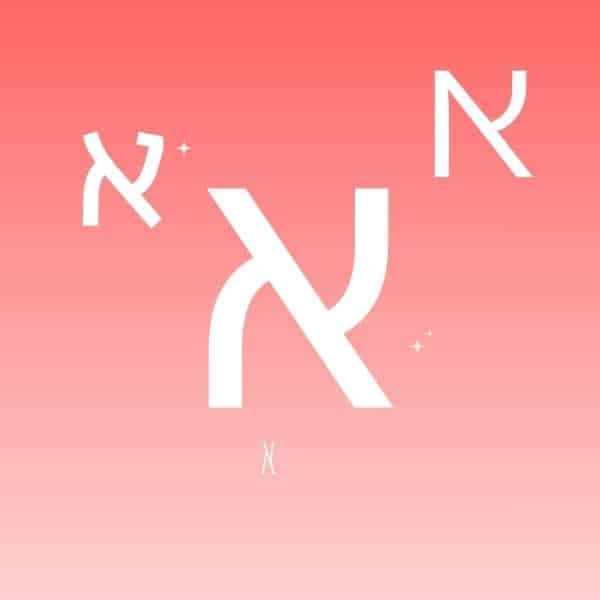
עיצוב טקסט בעברית הוא אמנות בפני עצמה, המשלבת בין קריאוּת, רגש ואסתטיקה טיפוגרפית. טקסט מעוצב היטב לא רק נראה טוב הוא מעביר מסר, יוצר תחושה ומוביל את הקורא להבין את הרעיון שעומד מאחוריו.
בבסיסו של כל עיצוב טקסט עומדים בחירת הפונט, גודל האות, היחסים בין שורות ופסקאות והקונטרסט בין צבעים. הפונט הוא לא רק אלמנט גרפי הוא השפה החזותית של המסר.
בעולם שבו אנו נחשפים למאות מסרים ביום, עיצוב נכון של טקסט בעברית הוא מה שמצליח לגרום למילים לבלוט, לעורר רגש ולשדר מקצועיות.
במאמר זה נעמיק בעקרונות עיצוב טקסט בעברית, נבחן כיצד לבחור את הפונט הנכון ונראה איך לשלב בין קריאוּת, סגנון וייחודיות ליצירת חוויית קריאה נעימה, עקבית ובלתי נשכחת.
בעידן שבו מרבית התוכן נקרא על מסכים, עיצוב טקסט בעברית באופן מדויק הוא גורם מכריע. טקסט שנראה טוב על דפדפן, ברשתות חברתיות או במצגות עסקיות – מגדיל את המעורבות ומשפר את חוויית המשתמש.
בעת עיצוב טקסטים בעברית, יש לשים לב למרווחים בין האותיות, לצפיפות השורות, לניגודיות בין צבע הרקע לצבע הפונט ולפריסת הפסקאות.
גם הבחירה בין יישור לימין, למרכז או לשמאל משנה את האופי של הקריאה. פונט נכון מעניק לטקסט קצב הרמוני, ומאפשר לקורא להתרכז במסר ולא במראה.
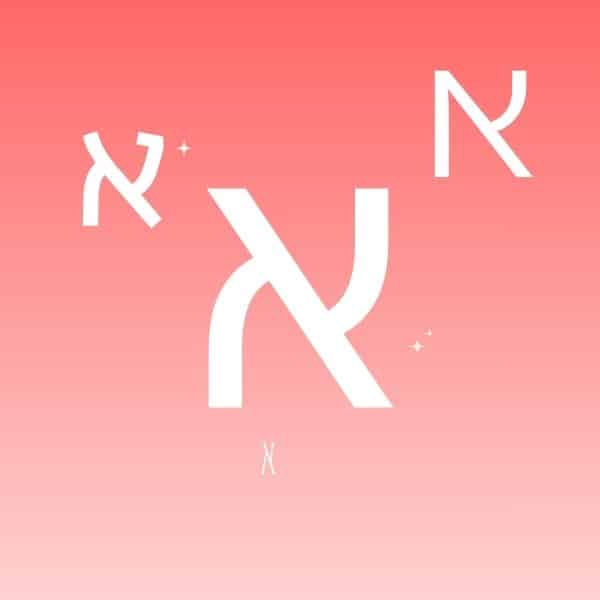
עיצוב טקסט בעברית מציע עושר טיפוגרפי ייחודי שאין בשפות אחרות. האותיות המרובעות, הזרימה מימין לשמאל והניקוד מאפשרים למעצבים לשחק עם סגנונות שונים מבלי לאבד את הזהות העברית.
היתרונות הבולטים של פונטים בעברית:
לדוגמה, רשימה של פונטים עבריים פופולריים לעיצוב טקסט בעברית:
עיצוב טקסט בעברית הוא יותר מאסתטיקה – הוא הדרך שבה המילים מדברות לקורא. כל בחירה טיפוגרפית משדרת רגש, ערכים ואופי.
הפונט הנכון יכול להפוך טקסט רגיל למסע חזותי מרגש, בעוד שפונט לא מתאים עלול לפגוע באמינות או בקריאות.
כשמשקיעים מחשבה בפרטים – מגודל האות ועד לצבע ולרווחים – נוצרת חוויית קריאה מקצועית, קלה ובלתי נשכחת.
בין אם אתם מעצבים אתר, מצגת או מסמך שיווקי, הקפידו לבחור פונטים בעברית שנראים גם איכותיים שידברו באותה שפה עיצובית כמו התוכן שלכם.
כן, אך במידה. שימוש בשני פונטים לכל היותר – אחד לכותרות ואחד לטקסט רץ – יוצר היררכיה חזותית נעימה בלי לבלבל את הקורא. חשוב שהפונטים ישתלבו בסגנון זה עם זה.
בעיצוב טקסט בעברית בדרך כלל מומלץ להשתמש בגודל של 16–18 פיקסלים לטקסט רגיל, ובכותרות גדולות יותר לפי רמת ההדגשה הרצויה.